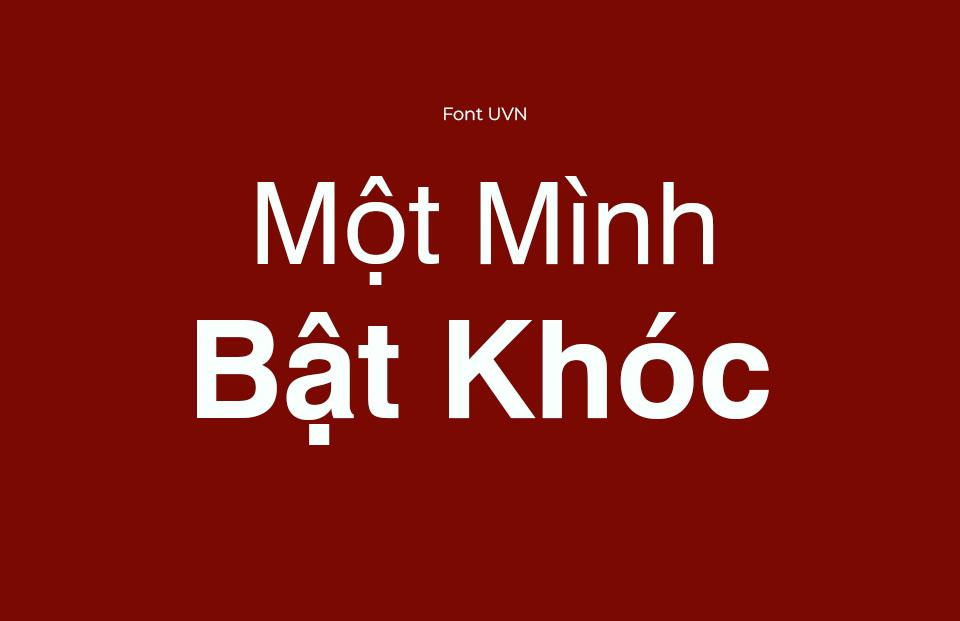
Bộ Font UVN Hồng Hà Full Việt Hóa
Font UVN Hồng Hà
Tác giả: UVN Hồng Hà
Bộ Font: UVN
Phân loại: Cá tính
Kiểu chữ: Có chân
Độ dày: Regular, Bold, Italic
Font UVN Hồng Hà
Bộ Font UVN Hồng Hà Full Việt Hóa là một bộ font chữ đa dạng, thuộc bộ font UVN. Được thiết kế với mục tiêu mang lại sự tinh tế và thanh lịch, bộ font này phù hợp cho các dự án thiết kế như website, tài liệu, và bao bì sản phẩm. Với các nét chữ rõ ràng và độ dày đều đặn, Bộ Font UVN Hồng Hà Full Việt Hóa không chỉ dễ đọc mà còn tạo cảm giác chuyên nghiệp. Việc Việt hóa font giúp người dùng dễ dàng sử dụng trong các thiết kế tiếng Việt, mang lại sự tiện lợi và thẩm mỹ cao.